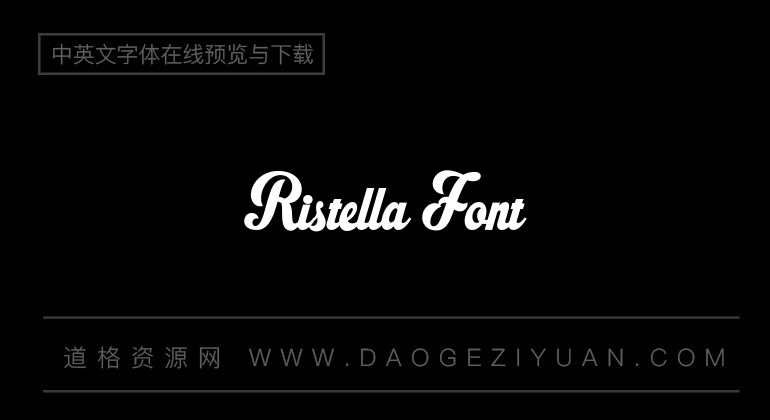
Ristella Font
Ristella Font是一种华丽的手写体字体,由设计师Thirtypath创建。该字体包括大写和小写字母、数字、标点符号和特殊字符。Ristella Font的设计风格充满了优雅和精致,适用于印刷品、品牌、包装设计以及其他需要富有时尚感和设计感的项目。该字体的优点是易于阅读,具有一定的个性和独特性,同时也兼具了一定的专业性和商业性。Ristella Font可用于个人和商业项目,也可以作为设计师的常用字体库之一。
Ristella Font是一款非常不错的手写艺术字体,具有很好的视觉感,适合于文化类的宣传设计、商业类品牌的广告和产品包装设计以及个性化文字排版等较多场景。